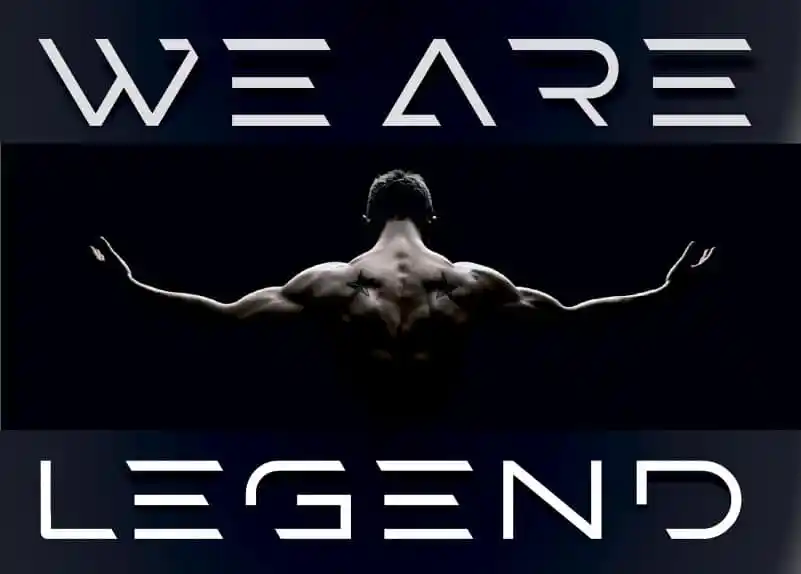
A STEPS Display Font é uma fonte com traços finos que mergulha no novo século moderno. Seu design elegante traz ao leitor a sensação vibrante e futurista de letras imponentes. Esta fonte é perfeitamente adequada para um vasto número de projetos, desde frases chamativas até bandagens fashion, vestuário e convites personalizados. Também se encaixa em cabeçalhos de blogs, panfletos, invitations e estilos gráficos de escrita. Com a STEPS Display Font, você pode dar um salto moderno para seu próximo projeto visual.